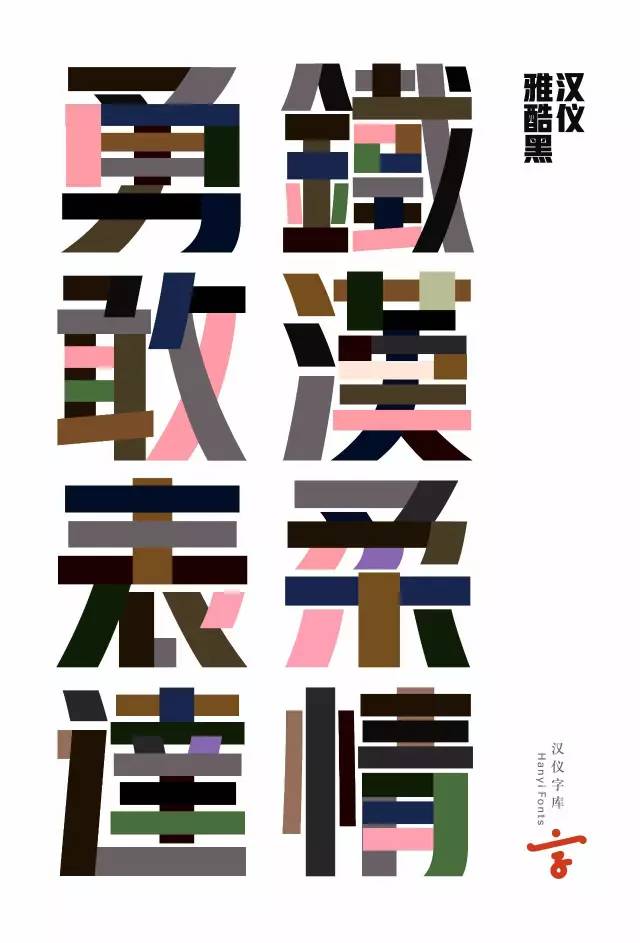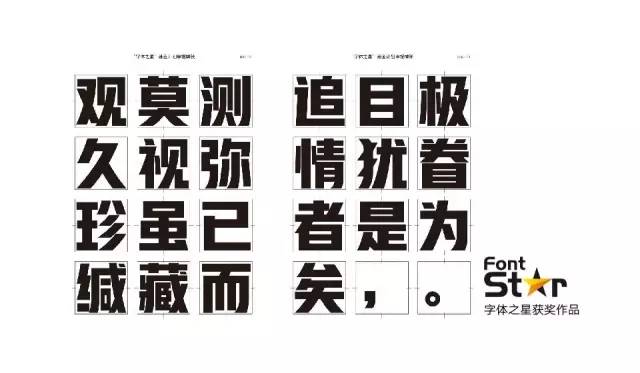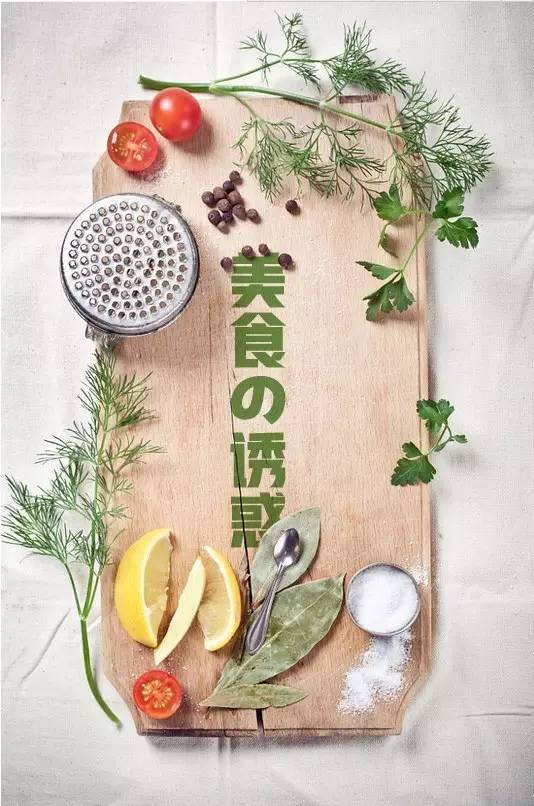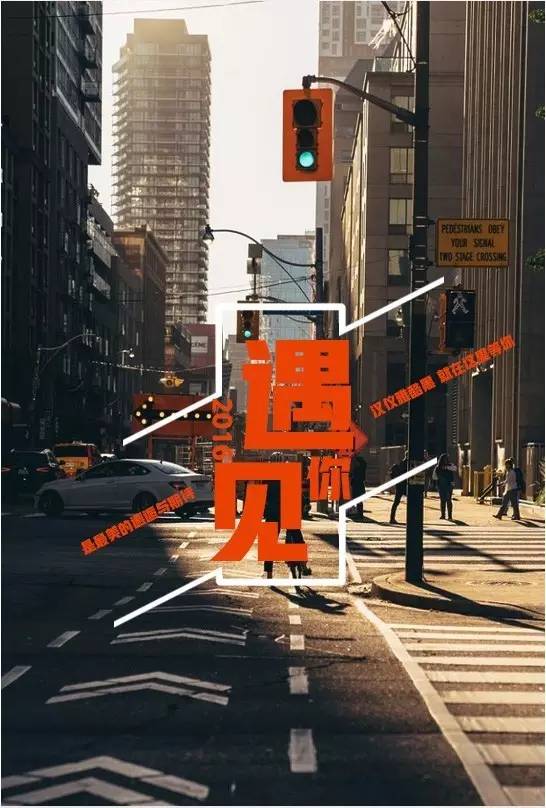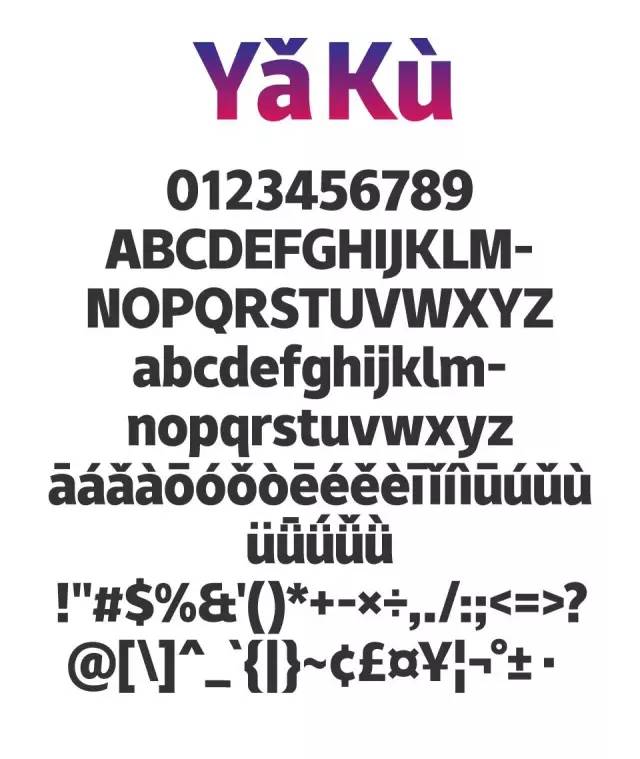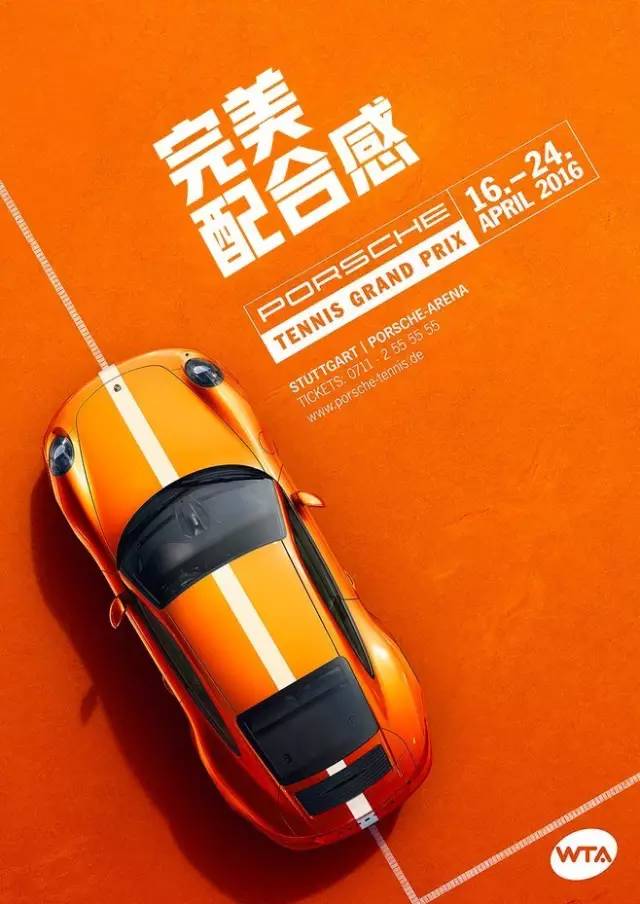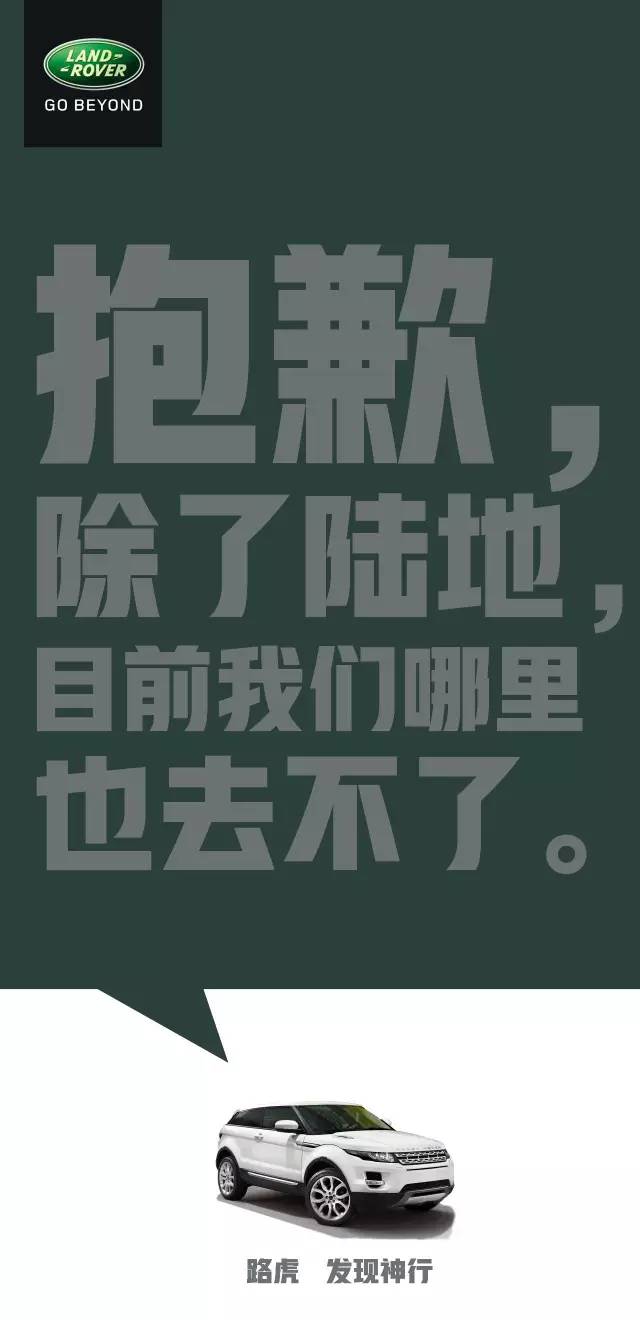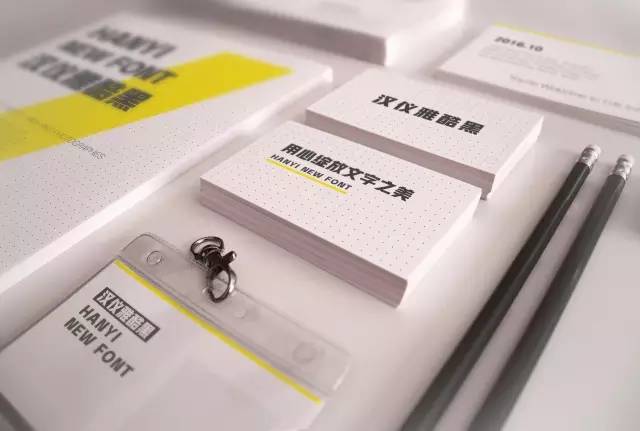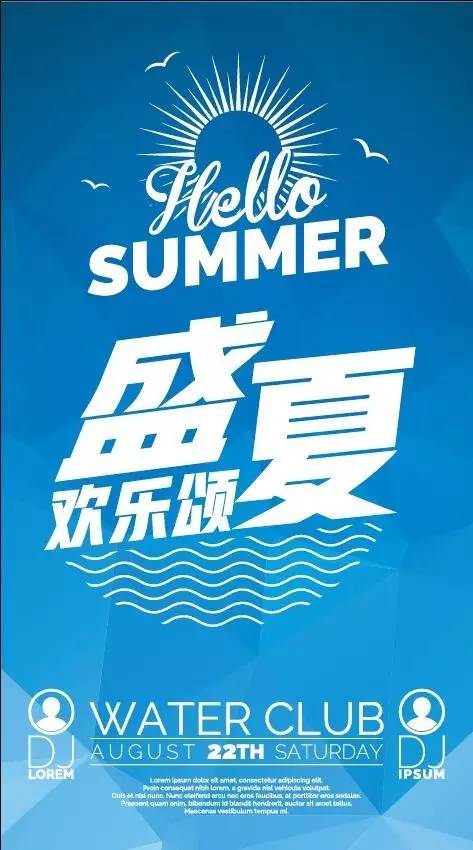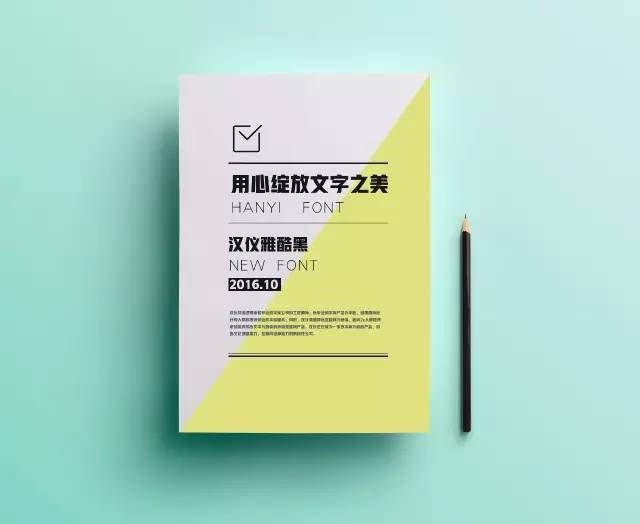
汉仪雅酷字体介绍,汉仪雅酷适用场景、使用案例。
在我从事广告创意设计的漫长的十多年的职业生涯里,作为一名Art Director,除了在画面调性风格的把控上需要倾注心力外,能否找到与画面风格匹配的标题字体曾让同行们煞费苦心,前几年想找到一款特殊些的标题字体很难,市场上就那么几款字体用来用去,大家早已出现严重的审美疲劳可又无新字可用。这是我自己动手设计这款字体的初衷。主创设计师-郝君军
没错,
这是一款刚柔相济,酷酷的标题字
如你所见
这又是一款不折不扣的获奖作品
首届汉仪字体之星大赛
寻找“菱心”标题字三等奖
设计特点
笔画的平行设计,
令标题综艺也有了手写味道,
如同横排笔刷的杰作。
92%的字面大小,
让粗壮的字与字之间达到均衡的分白效果。
有作为标题绝佳的整体感。
略高于普通视觉重心的设计,
让字看起来更精神,
更挺拔。
粗壮的标题字,
做字难点正在于此。
虽说是黑体但笔画之间会因为其重要性的区别有所调整。
笔画的特殊处理也是为了能够达到更好的识别效果。
块面感更强,
块状视觉冲击力更利于延展变形。
应用范围
标题 / 包装/ 电商
体育/运动/汽车/重工/互联网/科技/男性…
汉仪雅酷黑 | HYYaKuHeiW
资深广告创意人,字体设计师
汉仪字库签约字体设计师
早年辗转于国内及国际知名4A广告公司,
主要为医药、汽车、IT、通信等领域提供创意服务。
近年致力于图形及字体设计研究,擅长传统元素的现代表达,
用设计记录生活,表达观点。
2005年|作品入选中国创意年鉴
2006年|作品入选华文设计年鉴
2008年|作品入选ADS OFTHE WORLD
2012年|独立完成方正尚酷体设计
2011年|入选Hiiibrand国际品牌标志设计大赛
2013年|“字汇”中美两国字体海报展
2013年|汉仪首届《字体之星》字体设计大赛 银奖
2015年|作品入选第十届澳门设计双年展
2015年|作品参展《旅顺吼》海报展
2016年|汉仪第二届《字体之星》字体设计大赛标题组/正文组铜奖 评委奖
2016年|第八届《方正奖》字体设计大赛英文类优秀奖
2016年|字体作品入选华人设计圈权威品牌字体年鉴《Typography字体呈现》
中文设计团队
黄珍元 / 张延辉 / 冯志江 / 石凯 /
张亦曼 / 谭泽源 / 滕待茜 / 邴夏青
拉丁文设计
刘嫣然
团队感言
黄珍元
秉承标题字一贯的醒目特征。雅酷黑粗重饱满的笔画结构,简洁明了的横竖笔画,优雅张力的撇捺笔画,简练而不简单的笔画设计,赋予了它时而酷劲十足时而文艺清新的性格,就像硬汉也有柔情的一面。方正饱满的结构,形成整齐划一的排版效果,提高了标题字的阅读效果。
张延辉
雅酷黑像是大刷子刷出来的图形,笔画更加简洁充满张力。
冯志江
黑与白,直与弯,普通的元素构成独特的字体。
石凯
针对雅酷黑所有下沿线位于同一水平线上,设计师在海报制作和商业宣传册中可以简单的控制所有字的下沿线保持一致,只需简单的将字体做拉伸倾斜的变形即可制作出想要的视觉效果。同时这款字具有很强的可塑性笔画的延展及变形在原有字型基础上都可简单实现。
张亦曼
雅酷黑是一款字形方正,酷劲十足又不失韧性和优雅的字体。笔画简练,结构方正,在钩的笔画做了简化处理,融入了图形设计的手法,弧线顺滑,爽朗有张力,让整个字体充满时尚感。是一款兼具稳重优雅,以及灵动时尚的字体。在参与制作这款字体时,为保持字体饱满度,需要把每个字的上下边缘严格顶框,并且要保持字体笔画的粗度,同时要兼顾布白均匀,因此在多笔画字中要做特殊处理,需要注重笔画粗细的调整,笔画避让关系。雅酷黑对竖钩均作了特殊处理,将钩简化,让字体富有图形感,并且整个字更显方正、稳重。在处理撇、捺等有弧线的笔画,放置锚点时尽可能每个笔画减少锚点,以保证线条的顺滑和弹性,让字体透出优雅和时尚感。因此雅酷黑不仅适合用于网络、电商等要求张力和凸显度的标题字,同时也可以适合于沉稳、庄重雍容的背景之中。
谭泽源
雅酷黑笔画粗壮有力,撇捺具有优美的弧线,整体设计趋于简洁,是一款优秀的美术字体。
滕侍茜
汉仪雅酷黑字形个性鲜明、厚重工稳。笔画清晰而饱满,刚毅而不失优雅。这款字体本身具有时尚感和稳重性,有极强的视觉表现力。
刘嫣然
雅酷黑西文字体尽可能地从中文吸收参考了一些特征。如和缓的笔划末端,几何化的字形,宽大的字面等,使其既与中文相和谐相一致,又符合西文的设计形式。